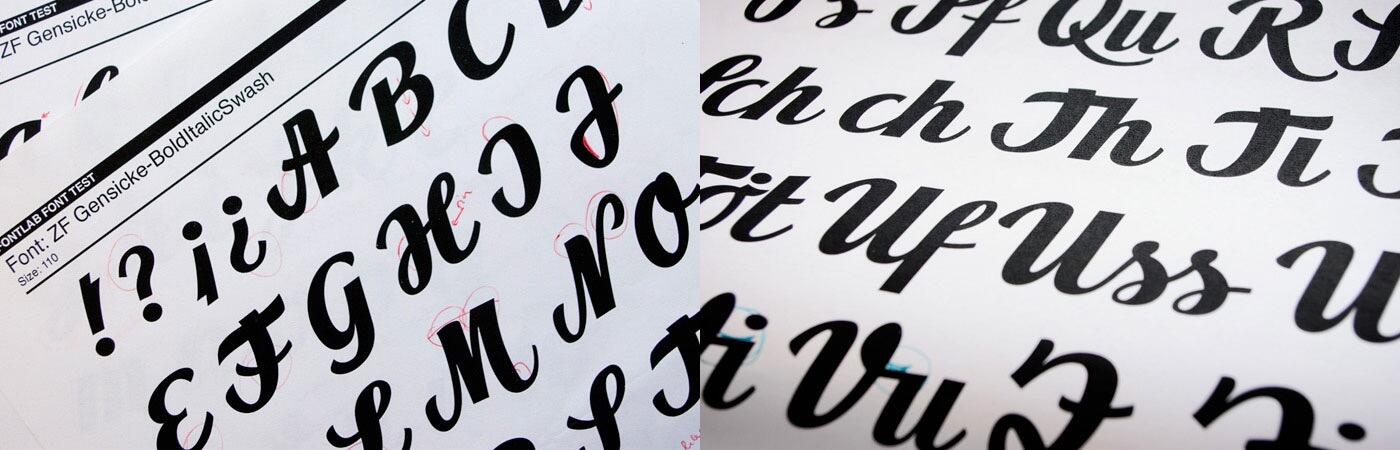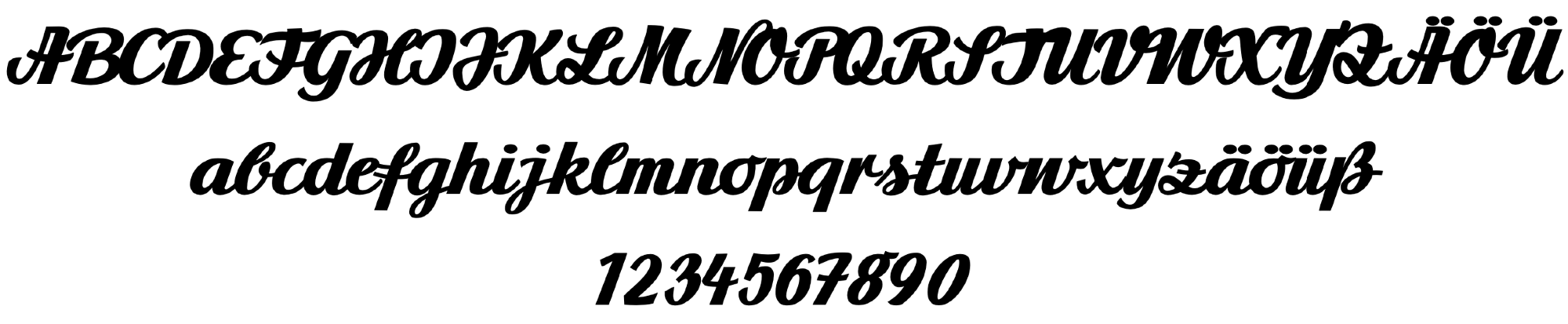
- Antiqua Schreibschrift
Die Gestaltung der ›Zierfische‹ basiert auf einem alten Schriftzug einer Berliner Tierhandlung. Entworfen und gezeichnet wurde der Schriftzug »Zierfische« von Manfred Gensicke (*1934). Als gelernter Schrift- und Reklamemaler arbeitete er zwischen 1960 und 1995 in Berlin und ist für viele Beschilderungen im öffentlichen Raum verantwortlich. Der Zierfische-Schriftzug beruht auf seiner persönlichen Handschrift und wurde Anfang der 1980-er Jahre neu gezeichnet und angefertigt.
Mit einer Spendenaktion konnte das Berliner Buchstabenmuseum den Schriftzug im Jahr 2009 übernehmen und somit vor dem Verfall oder der Entsorgung retten.
Doch nicht nur der Schriftzug wurde gerettet. Der charakteristische Schildermaler-Schreibstil von Manfred Gensicke wurde mit dessen Unterstützung vom Designer Dirk Heider als komplette Schrift namens Gensicke ZF ausgebaut.
Eine besondere Herausforderung stellten die Buchstabenverbindungen dar. Durch unzählige Ligaturen, die sich per OpenType automatisch aktivieren lassen, spiegelt sich der lockere, handschriftliche Charakter auch in der Umsetzung als Font sehr gut wider. Nach dem Ende des Schriftanbieters Veer ist die Erhältlichkeit der Schrift unklar.